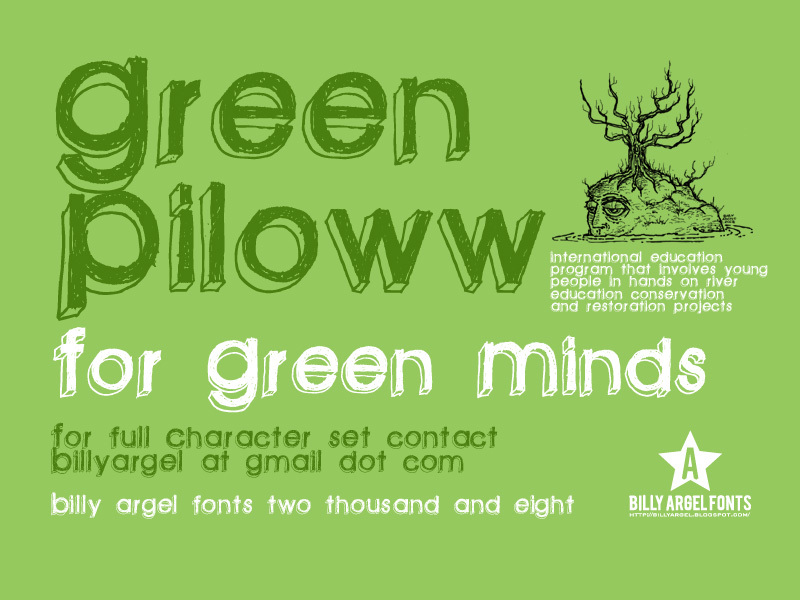
green piloww
Green Piloww, progettato da Billy Argel nel 2008, è un font 3D gratuito caratterizzato da contorni grezzi e doppi, con un ritmo vivace e disegnato a mano. I tratti sovrapposti creano un'ombra leggermente fuori registro, dando alle lettere arrotondate l'aspetto di un poster stampato in modo imperfetto.
Questo font gratuito è perfetto per locandine di concerti, grafiche skate, copertine di album, etichette streetwear, fanzine e titoli editoriali giocosi. Si presta meglio a brevi testi, dove i bordi stratificati conferiscono al titolo una sensazione tattile senza dover ricorrere a effetti extra.